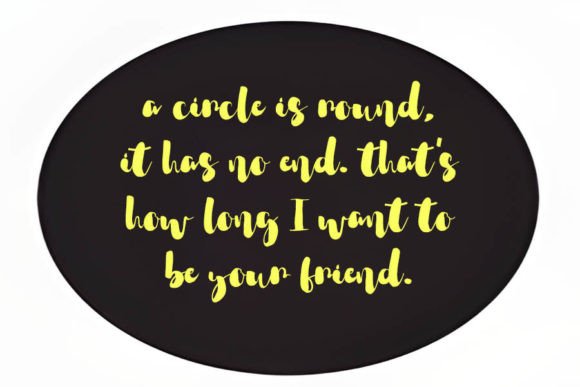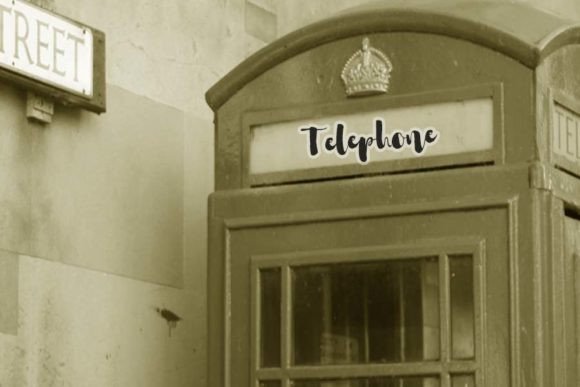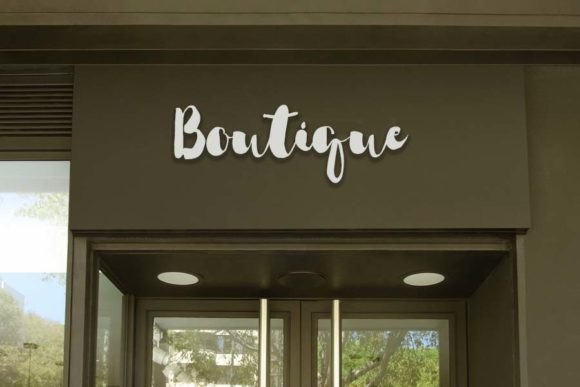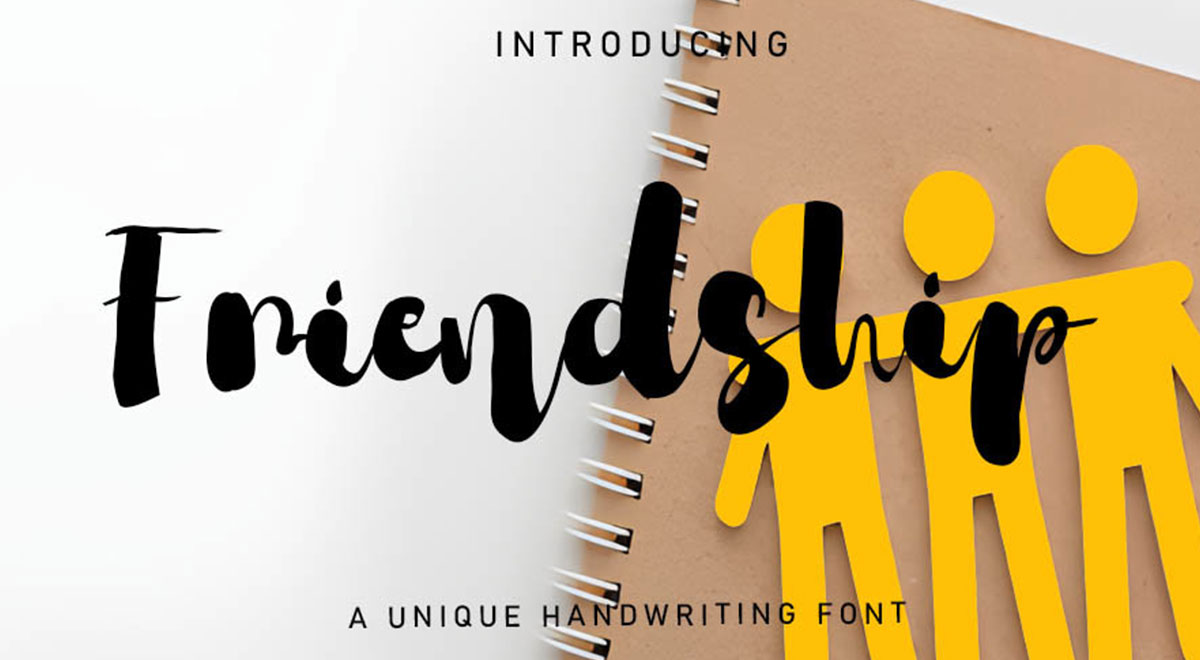
فونت Friendship انگلیسی
دانلود فونت Friendship انگلیسی Font فرندشیپ |
| ⭐ توضیحات | Friendship یک فونت دست نویس فوق العاده منحصر به فرد است. این فونت که استادانه طراحی شده است تا به یک مورد علاقه واقعی تبدیل شود، این پتانسیل را دارد که هر یک از ایده های خلاقانه شما را به بالاترین سطح برساند! |